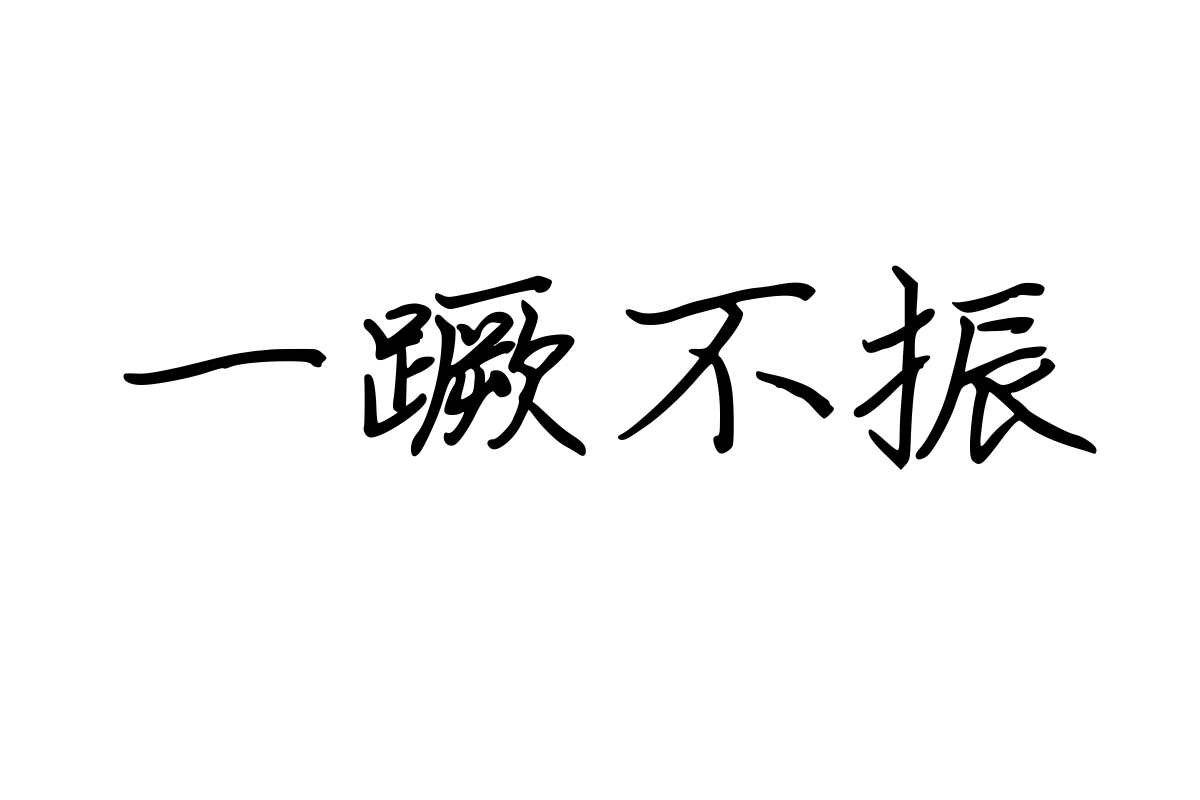
蝉羽浮生雪媚是一款书法字体,由汉仪字库出品。这款字体以蝉翼般轻盈的笔触、飘逸灵动的姿态,展现出一种独特的美感和韵味,给人以视觉上的享受和心灵上的触动。
特点:
1. 线条流畅:蝉羽浮生雪媚的笔画线条流畅自然,给人一种优雅而不失灵动的感觉。
2. 结构紧凑:该字体的结构紧凑,每个笔画都恰到好处地分布在字形中,使得整个字体看起来更加协调统一。
3. 风格独特:蝉羽浮生雪媚融合了传统书法与现代审美的元素,既有古典的韵味,又不失现代的时尚感。